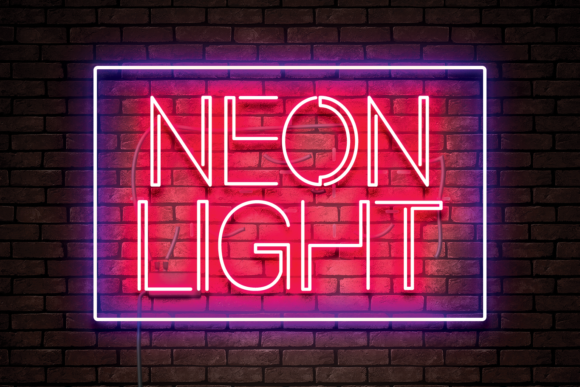
Neon Light Font
Neon Light Font – اجعل تصاميمك تتوهج بأسلوب عصري!
استمتع بتجربة تصميم فريدة مع Neon Light Font، الخط المثالي لإضافة لمسة من الإضاءة النيونية الجذابة إلى مشاريعك. يتميز هذا الخط بأسلوب عصري وأنيق يحاكي إضاءة النيون الواقعية، مما يجعله مثاليًا لتصميم الشعارات، الإعلانات، منشورات السوشيال ميديا، البوسترات، وغيرها الكثير.
???? مميزاته:
✅ تصميم احترافي يحاكي تأثيرات النيون الحقيقية
✅ مناسب لمشاريع العلامات التجارية والإعلانات البصرية
✨ أضف لمسة من التألق والحيوية إلى تصاميمك مع Neon Light Font واجعلها تضيء بإبداع! ✨